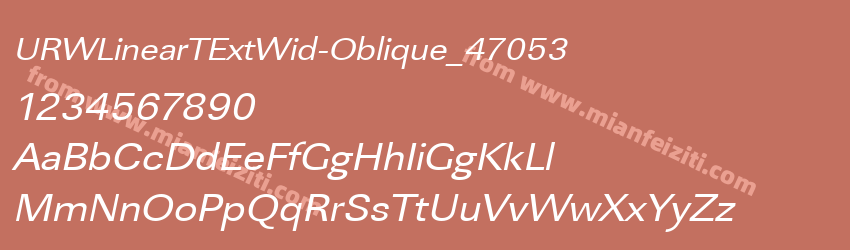
URW LinearT Regu Extr Wide Obli
字体名称: URW LinearT Regu Extr Wide Obli
Postscript名称: URWLinearT-ReguExtrWideObli
字体版本: Version 001.005
字体字重: Oblique
本款“URW LinearT Regu Extr Wide Obli”是一款书写很新颖的字体,字体大方,适合各种设计作品使用!欢迎下载!